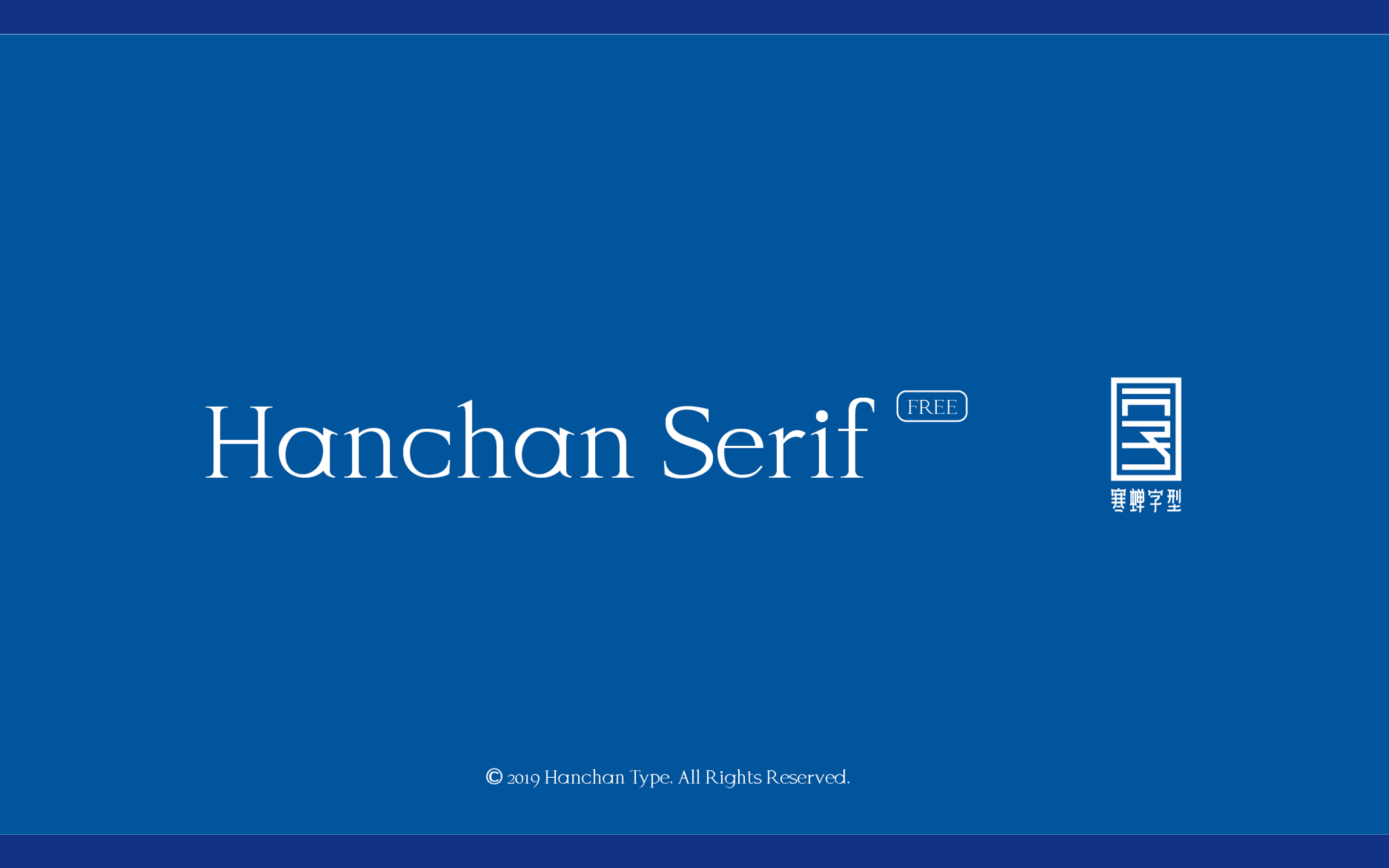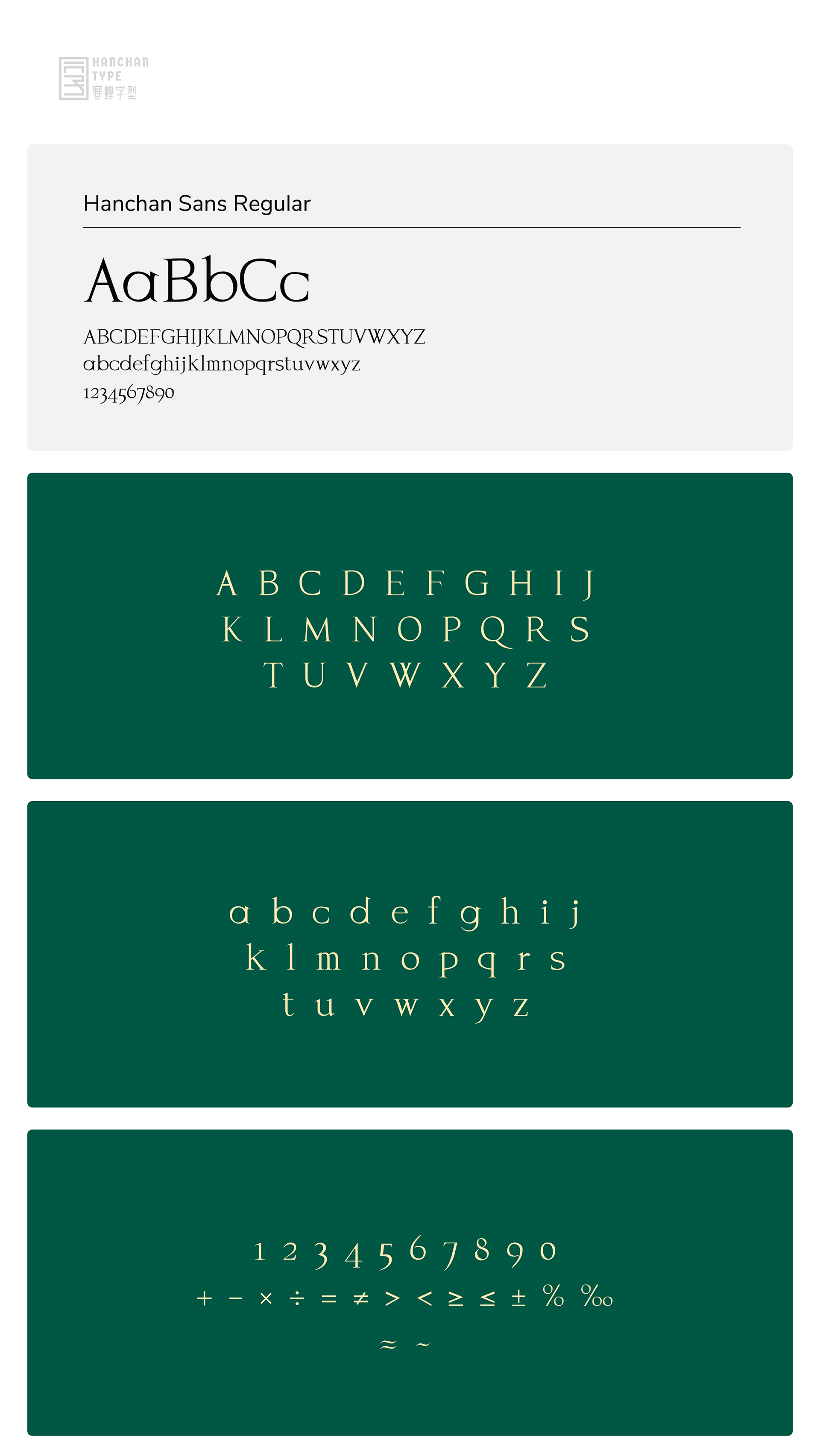
Hanchan Serif 免费商用英文字库下载
Hanchan Serif 是站酷网友萧熠Siue发布的一款免费商用衬线体风格英文字体,可与 Hanchan Sans (无衬线体)配合使用,该字体是寒蝉字型中的一款高质量衬线体英文字体;字体结构稳重大气,适用范围广。
Hanchan Serif 免费商用英文字库,字形预览